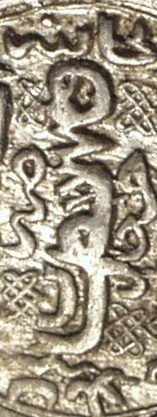
| 資料名 | イル・ハン朝貨幣1 |
| 文字/言語 | 表:アラビア文字/アラビア語 裏:アラビア文字・ウイグル文字 /アラビア語・モンゴル語 |
| 材質/形態 | 銀/円形コイン(打刻) |
13〜14世紀にイランを中心とする地域に栄えたイル・ハン朝
の貨幣。第9代ハーンであるアブー・サイードの名を冠している。
表面にはアラビア語の定型句、裏面の中央にはウイグル文字で